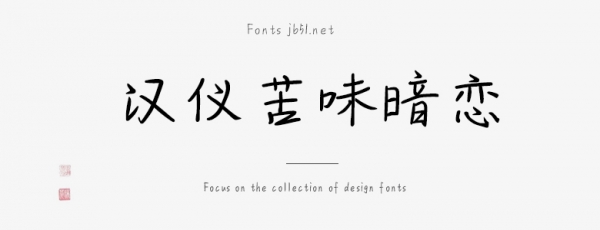
漢儀苦味暗戀簡(jiǎn)是由漢儀字庫(kù)出品,字體筆觸纖細(xì),書(shū)寫(xiě)流暢,具有很好的視覺(jué)感,適合應(yīng)用于藝術(shù)設(shè)計(jì)、平面宣傳設(shè)計(jì)、網(wǎng)頁(yè)設(shè)計(jì),書(shū)法字帖等領(lǐng)域,需要的朋友可以前來(lái)本站下載。